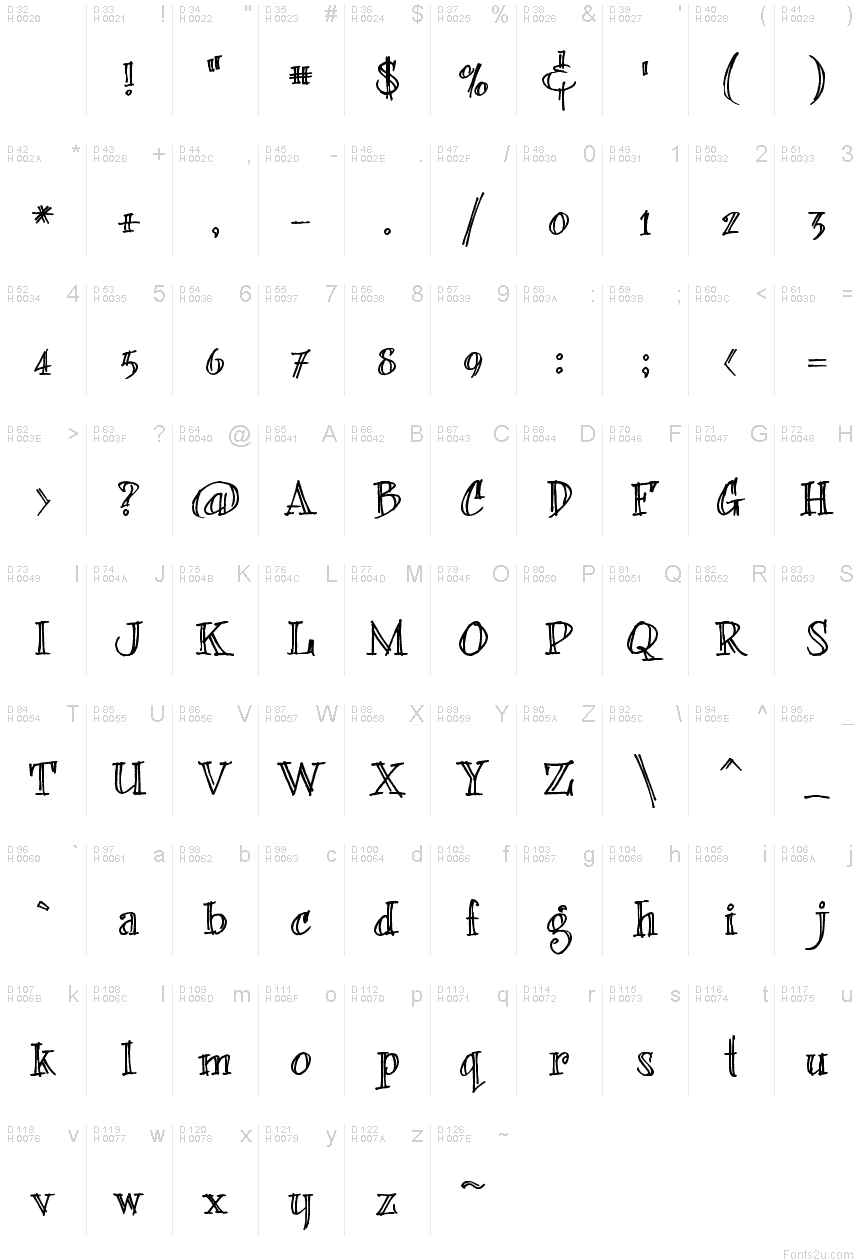
bearerFond 字体
bearerFond
JOEBOB Graphics
JJW van der Ham
由 J O E B O B graphics 的 JJW van der Ham 设计的 BearerFond 字体,具有一种松散的墨迹韵律感,仿佛是用粗记号笔在粗糙纸张上随手涂鸦而成的。不均匀的笔触、俏皮的起伏和略显歪斜的曲线,赋予每个字词一种友善且纯手工的质感。这是一款免费的手写字体,能瞬间为你所排版的任何内容增添个性。
使用 BearerFond,你可以为演出海报、小志 (zine)、独立书籍封面、剪贴簿标题、儿童项目,以及手工或 DIY 商店的品牌设计,增添一种独特且富有人情味的触感。这款免费字体在放大使用时效果极佳,能够清晰展现其草图般的细节,并且与用于正文或说明文字的简洁无衬线字体自然搭配。